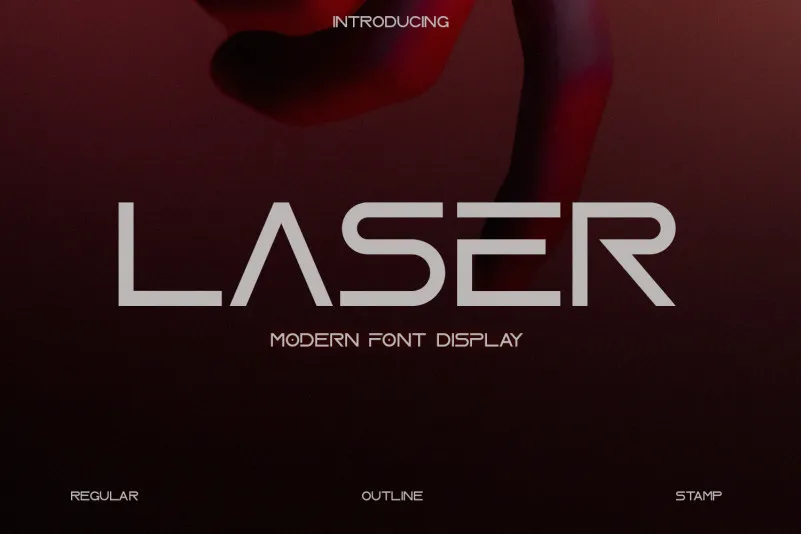
Laser Display Font – Download Grátis
A Laser Display Font é uma opção perfeita para criar designs modernos e elegantes em grande escala. Desenvolvida pela ari, esta fonte está especialmente projetada para tipos de serif livre, criando um efeito limpo e sofisticado. Suas variações regulares, outline e stamp oferecem uma versatilidade incomparável que se adapta perfeitamente para diversas finalidades gráficas como cartões de nome, outdoors, logomarcas, capas de revistas, banners e até mesmo camisetas. O aspecto clean e moderno da Laser Display Font torna-a ideal tanto para elementos pequenos quanto grandes. Seja em um design de nomecard detalhado ou em uma grande arte publicitária na frente do seu negócio, a Laser Display Font oferece os recursos necessários para que seus projetos atinjam o sucesso desejado. Com sua arquitetura limpa e elegante, esta fonte é uma escolha inegável para quem busca expressar um design moderno em grande escala.